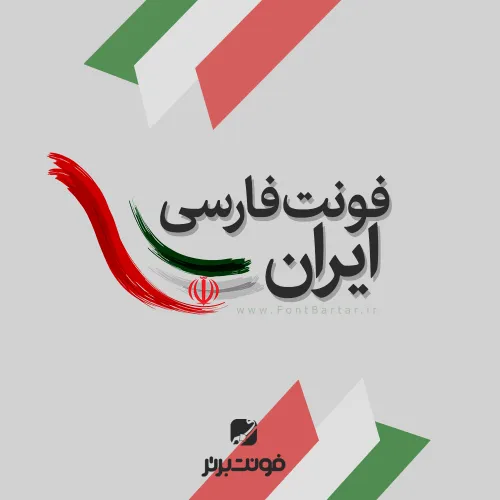
فونت فارسی ایران
فونت ایران
دانلود فونت جدید فارسی ایران ، فونت فارسی سیک و استاندارد مناسب برای استفاده در تایپ متن در دو وزن و با خوانائی بالا که هم اکنون در فونت برتر ضمن معرفی این فونت زیبا خدمت کاربران گرامی ، امکان دانلود رایگان ان را نیز برای شما محیا کرده ایم.
فونت فارسی ایران مورد استفاده برای:
- طراحان وب سایت و گرافیست های خلاق می توانند از این مجموعه زیبا فونت در طراحی پروژه های تبلیغاتی و تجاری خود کمک بگیرند.